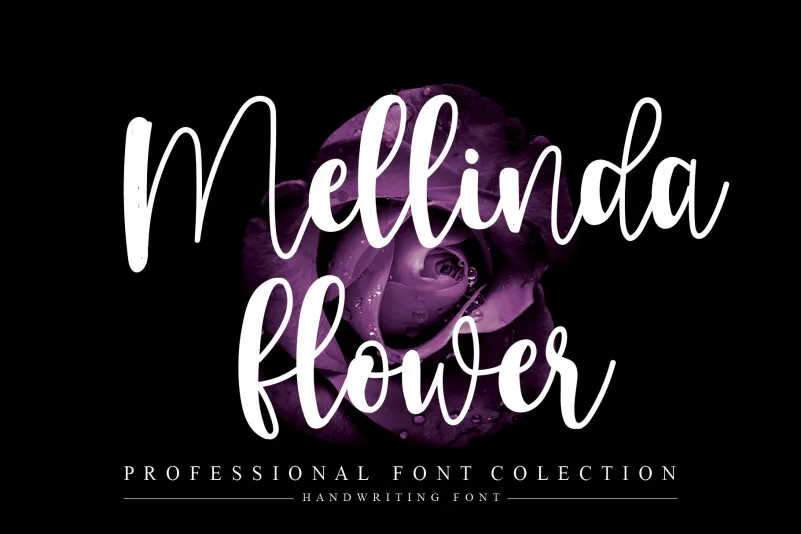
Mellinda Flower Script Font – Download Grátis
Mellinda Flower Script Font é uma elegante e delicada fonte escrita à mão. Seus caracteres distintos e bem redondos fazem dela uma obra-prima. Adore a versatilidade impressionante dessa fonte e use-a para criar designs excepcionais. Aproveite suas formas curvilíneas e coloridas que lembram as flores frescas, adequada tanto para aplicações de moda quanto design gráfico e personalização de produtos. Esta fonte é perfeita para quem procura uma maneira criativa de dar vida aos textos, sem abrir mão da elegância e sofisticação típicas do estilo escrita à mão. Ideal para criar um toque pessoal em qualquer projeto, seja ele gráfico, editorial ou digital.